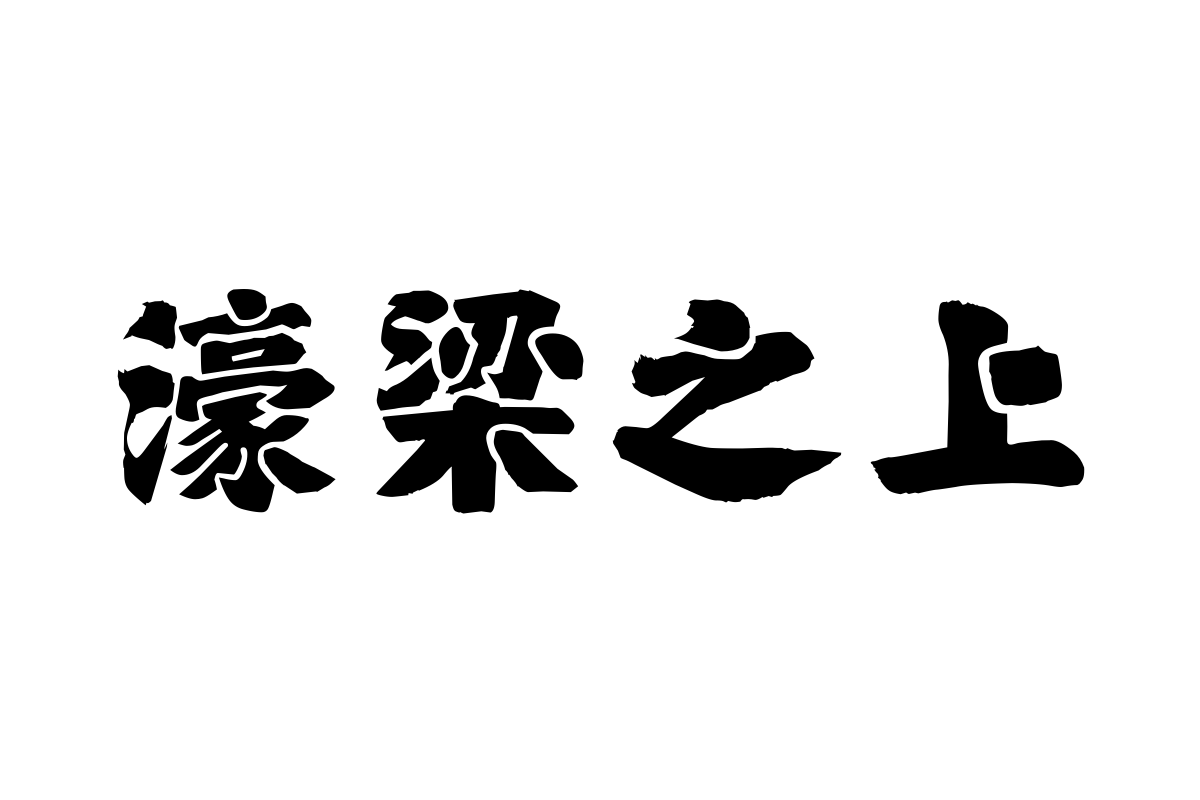
汉仪麒麟体繁是一套中文字体,由汉仪公司设计。这套字体以其独特的风格和视觉效果而著名,被广泛应用于各种印刷品、广告、网站等。
汉仪麒麟体繁的特点是字形独特,线条流畅,具有很高的辨识度。它的笔画粗细变化丰富,既有粗犷的线条,也有细腻的部分,使得整体效果既有力量感,又不失优雅。此外,这套字体还注重细节的处理,如笔画的连接处、字与字之间的间距等,都经过精心设计,使得整体效果更加和谐。
汉仪麒麟体繁适用于需要强调个性和创意的场合,如企业宣传、品牌标识、海报设计等。它的使用可以提升作品的视觉冲击力,增加作品的艺术感。同时,由于其独特的设计风格,也常被用于一些特定的主题或文化元素中,如古典文学、民间艺术等。